任平,著名书法家、书法教育家,现为中国硬笔书法家协会副主席,曾获全国书法大赛特等奖3次,多次担任全国书法大赛评委。出版练字字帖40余种,作品在国内外展出,被文化教育权威机构收藏。《名家钢笔行书步步高教程-间架结构》分基本笔画、偏旁部首、间架结构(附章法说明及创作示范)三册,合理编排。本字帖是其中的间架结构一书。它所选的例字较同类的字帖多,且都是经过仔细筛选的有代表性的常用汉字。建议将三本字帖结合起来使用,适合于高中生、大学生、白领系统的练字的时候使用。
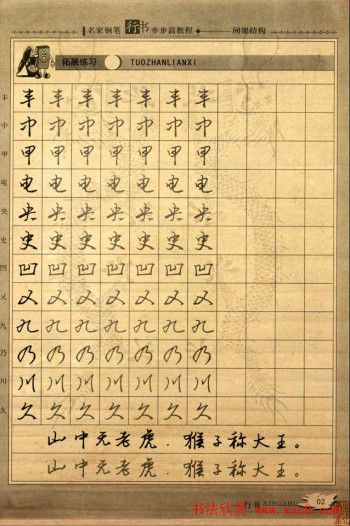
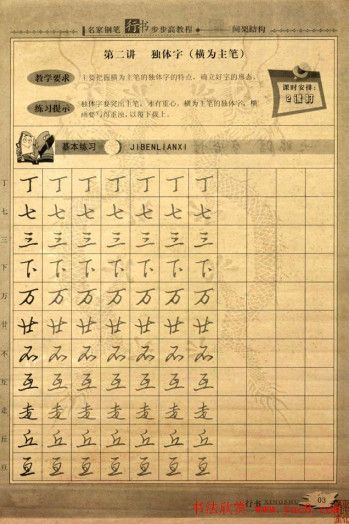
行书的用笔较楷书简洁,它不同于楷书将字的每个点画都交代清楚,而是加以适当简化,或者省略某些笔画,如钩、挑等,或者合并、替代一些笔画,甚至部分采用草书的写法。
行书用笔最大的特点是点画较多的牵丝、映带。牵丝是指上一笔和下一笔之间顺应笔势而出的细线,使点画间显表现出相互响应的关系,有时也将零散的点画通过牵丝连接起来,使得字体茂密。
本教材特别约知名的书法家黄建新讲解、任平书写行书,豪迈洒脱,书写漂亮!只要认真练习,相信大家会享受到全面系统而又阶梯式提高书写水平的快乐。